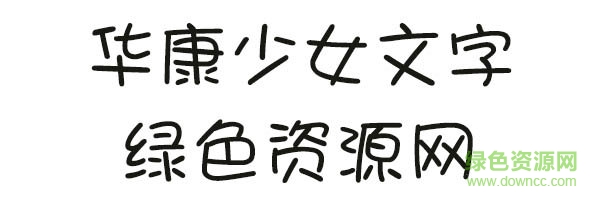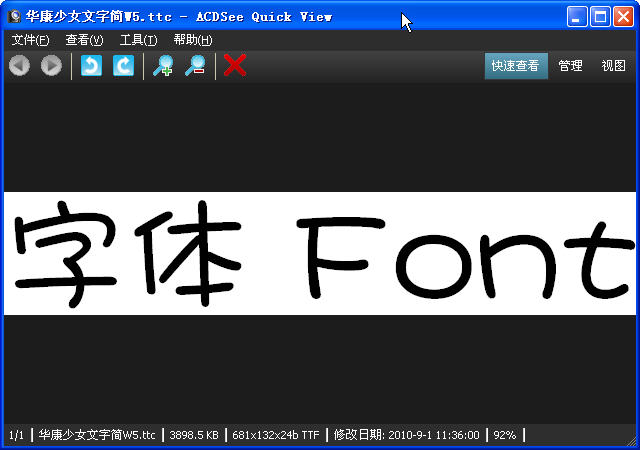
華康少女文字w5由綠色資源網(wǎng)為您提供下載資源,這款優(yōu)秀的字體是一位天真活潑的少女所開發(fā)而來,字型中充滿年青人蓬勃的氣息與自由奔放的性格,是華康字型中最受用戶喜愛的字型之一,需要的用戶快到綠色資源網(wǎng)下載體驗吧!
華康少女由一位少女開發(fā)而來的,字型活潑可愛,充滿了青春的氣息,常用于漫畫、旅游、電視廣告以及一切有關(guān)動感、歡樂、青春的題材上,是用戶最喜愛的字體之一。